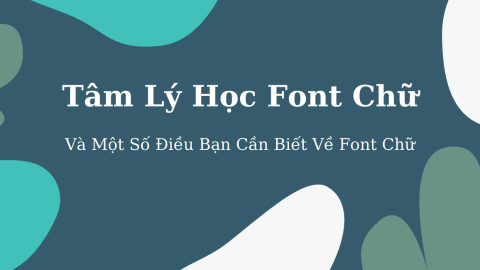
Bạn có biết rằng trên thế giới có hơn nửa triệu font chữ. Mặc dù các website hầu hết được xây dựng trên một số loại font chữ khá phổ biến, có thể nói font chữ cũng được xem là một yếu tố hình ảnh, bạn có thể sử dụng chúng như là các yếu tố tâm lý để vẽ nên một câu chuyện giúp hỗ trợ đắc lực cho website của bạn. Giống như các yếu tố thiết kế khác, font chữ ảnh hưởng đến người đọc, giúp họ cảm nhận được văn bản, sản phẩm, hay thậm chí là toàn bộ trang web. Do đó, việc lựa chọn font chữ thích hợp sẽ giúp gia tăng sự trải nghiệm của người dùng trên trang web của bạn.
Việc lựa chọn font chữ không phải là một điều dễ dàng. Trên thực tế, có thể mất rất nhiều tháng hoặc nhiều năm để chọn và thử các font chữ sao cho phù hợp và quá trình thử nghiệm liên tục này, thậm chí là những thay đổi chỉnh sửa nhỏ nhất cũng đã làm tăng hoặc giảm sự thành công của trang web của bạn.
Dưới bài viết hôm nay, hãy cùng với GenZ tìm hiểu sâu hơn về cách những font chữ hoạt động dưới cấp độ tâm lý và cách bạn ứng dụng yếu tố tâm lý từ việc chọn font chữ phù hợp cho thiết kế của mình nhé!
Khái niệm cơ bản về Typography
Typography là nghệ thuật trình bày và sắp xếp kiểu chữ để làm cho ngôn ngữ viết trở nên dễ đọc và hấp dẫn hơn đối với người đọc. Một phần của typography bao gồm nhiều kiểu chữ, hình thức, cấu trúc và phong cách khác nhau. Mỗi kiểu chữ bao gồm một số font chữ tuân theo một quy tắc khiến chúng trở thành một phần của một loại kiểu chữ cụ thể.
Font chữ là các yếu tố trực quan được sử dụng để truyền thông tin hoặc hiển thị nội dung cho người đọc. Font chữ cũng mang cho mình một thông điệp ẩn để thay đổi cách người đọc cảm nhận về bất kỳ nội dung chính nào đó trong văn bản.
Mỗi font chữ là một tập hợp các chữ cái duy nhất với những nhiều tính chất, độ rộng và hình dáng khác nhau. Tuy nhiên, một số font chữ cũng có những điểm tương đồng trong các thuộc tính trên và do đó tạo nên một kiểu chữ, một họ font chữ có nét liên quan.
Hãy xem điều gì tạo nên một font chữ và cách các font chữ đó được sử dụng trong thế giới kỹ thuật số hiện đại như thế nào.
Cơ thể con chữ
Một số kiểu chữ sẽ có những giới hạn chặt chẽ về những yếu tố bạn có thể thay đổi nhưng vẫn giữ trong một kiểu font chữ cụ thể và đối với những kiểu chữ khác thì sẽ có những quy tắc thoải mái hơn.
Một kiểu chữ bao gồm các phần khác nhau có thể phân biệt được, ví dụ như
- Serif: các chữ có ít dòng, nét hoặc có chân trên các mẫu chữ
- Sans – serif: không có chân trên các mẫu chữ
- Ascender: phần của con chữ nằm ở trên đường mean line như (h, l, k,…)
- Aperture: là độ mở các chữ cái như C,c S,s a và e
- Baseline: là một đường kẻ tưởng tượng nó là đường thẳng nối các phần chân chữ định hình trên một dòng kẻ và bất kỳ một chữ nào cũng nằm trên một đường gốc
- Cap height: chiều cao từ đường bên dưới đến phía trên cùng của một phông chữ in hoa.
- Descender: là điểm nối các điểm thấp nhất mà các chữ có thể tạo ra trên một dòng như (p, g, y,…)
- Stem: một nét chính
- Stroke: có thể là đường thẳng, đường cong và các đường nét trong một kiểu chữ có thể có độ đậm đồng nhất hoặc khác nhau
- X – height: đường gióng biểu thị chiều cao của chữ.
Hãy lấy kiểu chữ serif làm ví dụ. Để một font chữ phù hợp với họ font chữ serif, nó phải có serifs trên các thiết kế chữ cái. Chắc chắn, có nhiều danh mục con dưới một kiểu chữ với nhiều quy tắc khác nhau cho đến chi tiết, nhưng nếu kiểu font chữ sử dụng serifs, nó có thể nằm trong họ phông chữ nổi bật.
Tại sao Typography lại quan trọng?
Trong thế giới kỹ thuật số hiện nay, kiểu chữ không chỉ là việc chọn một font chữ đẹp. Việc chọn một kiểu chữ thích hợp cho thiết kế website của bạn cũng sẽ ảnh hưởng rất nhiều đến người đang quan tâm. Hơn nữa, một kiểu chữ đẹp và xuất sắc có thể tạo ra một hệ thống phân cấp trực quan, nó làm tôn lên được sự cân bằng và là trung tâm của thiết kế.
Bạn có thể thấy rằng một chiến lược sử dụng các kiểu chữ chuyên dụng nhằm mục đích:
- Tạo thương hiệu độc đáo
- Nâng cao trải nghiệm người dùng
- Ảnh hưởng đến mọi người thông qua cảm xúc
- Gây chú ý trực tiếp
Giống như việc thiết kế tổng thể cho website của bạn được phục vụ với mục đích kể một câu chuyện cho khách hàng, phông chữ chính là yếu tố hỗ trợ thêm cho câu chuyện. Và đó không chỉ là những gì bạn muốn người dùng của mình nhìn thấy, đó cũng là về cảm giác của họ khi đọc một nội dung nào đó và phông chữ giúp tạo ra cảm xúc mà bạn cần để phục vụ mục đích cho trang web của mình.
Những kiểu font chữ chính và tâm lý học font chữ
Theo nghiên cứu của Hiệp hội Tâm lý Học Anh Quốc vào năm 1989 đã phát hiện ra mối tương quan giữa các tính từ và các font chữ khác nhau bởi những người được tham gia thử nghiệm. những người này được cho xem nhiều kiểu chữ và được yêu cầu đánh giá chất lượng tri giác mà họ có thể sở hữu, chẳng hạn như nặng, nhẹ, nhanh và chậm.
Một nghiên cứu khác, để mở rộng sự lựa chọn tính từ của những người tham gia, và cuối cùng họ đã tìm thấy mối tương quan cao nhất với phông chữ Times New Roman và Helvetica. Cũng rất thú vị khi lưu ý rằng những phông chữ này nằm ở phía đối diện của phổ kiểu chữ, với Times New Roman là font chữ serif và Helvetica là sans-serif.